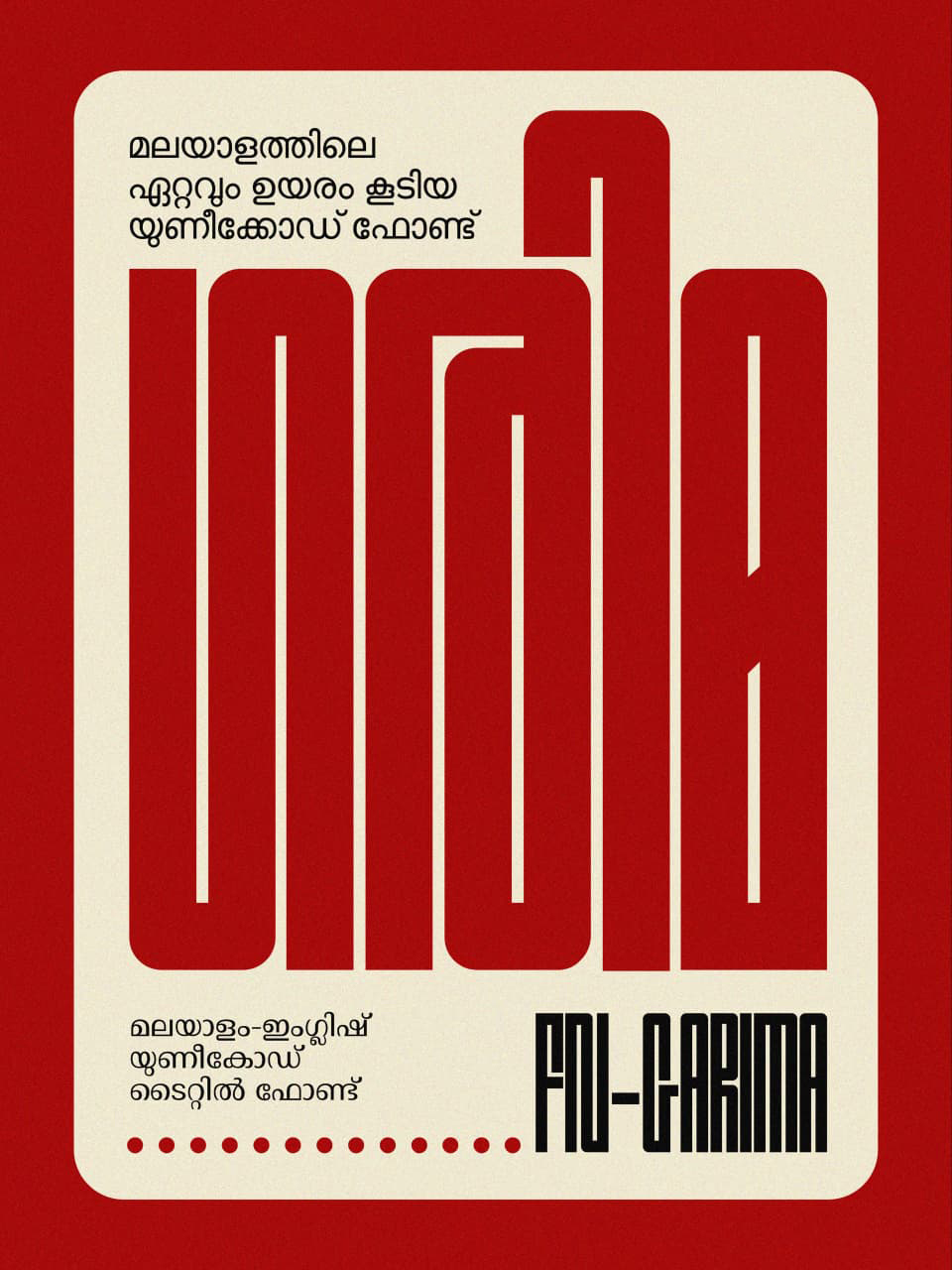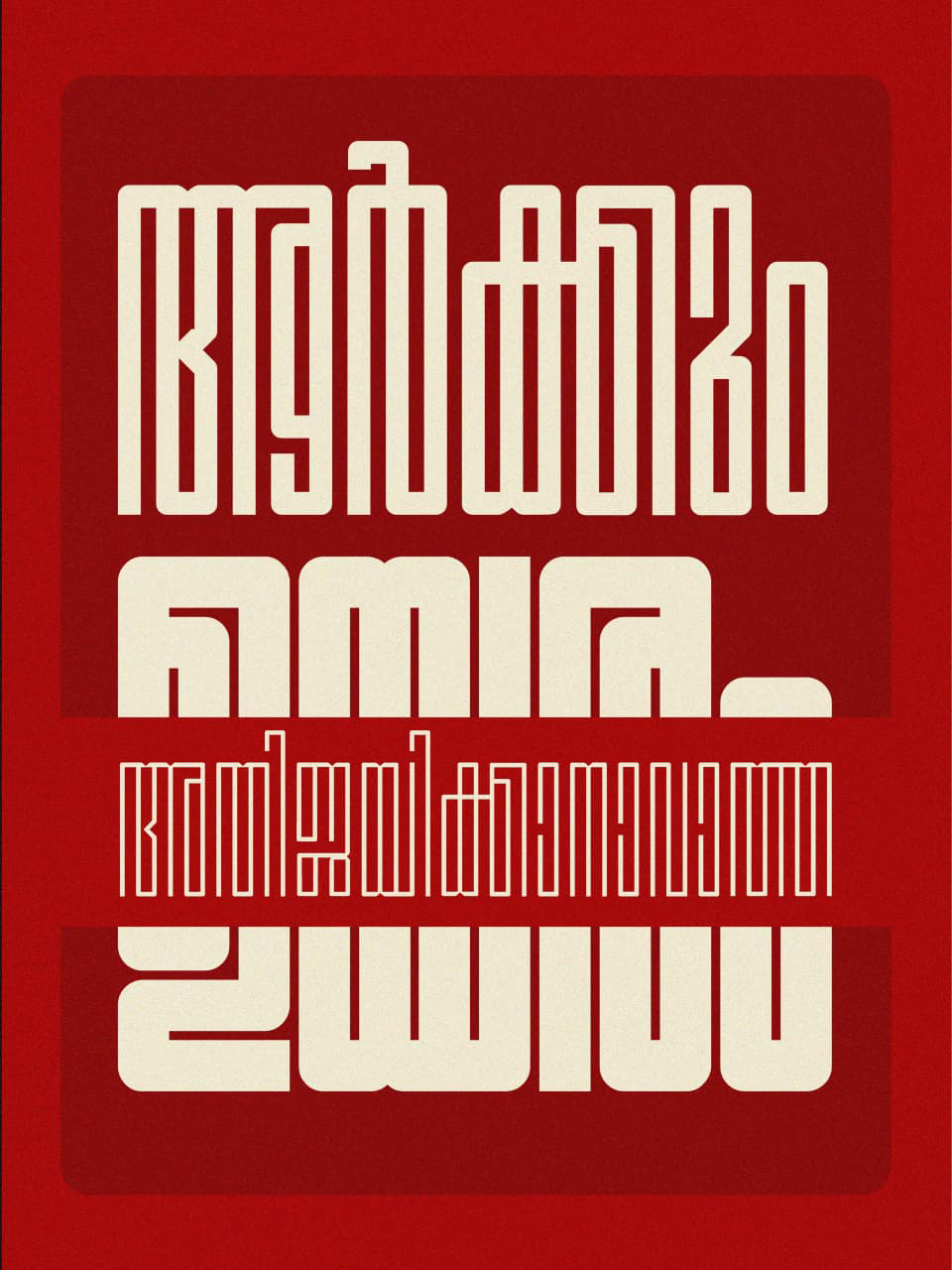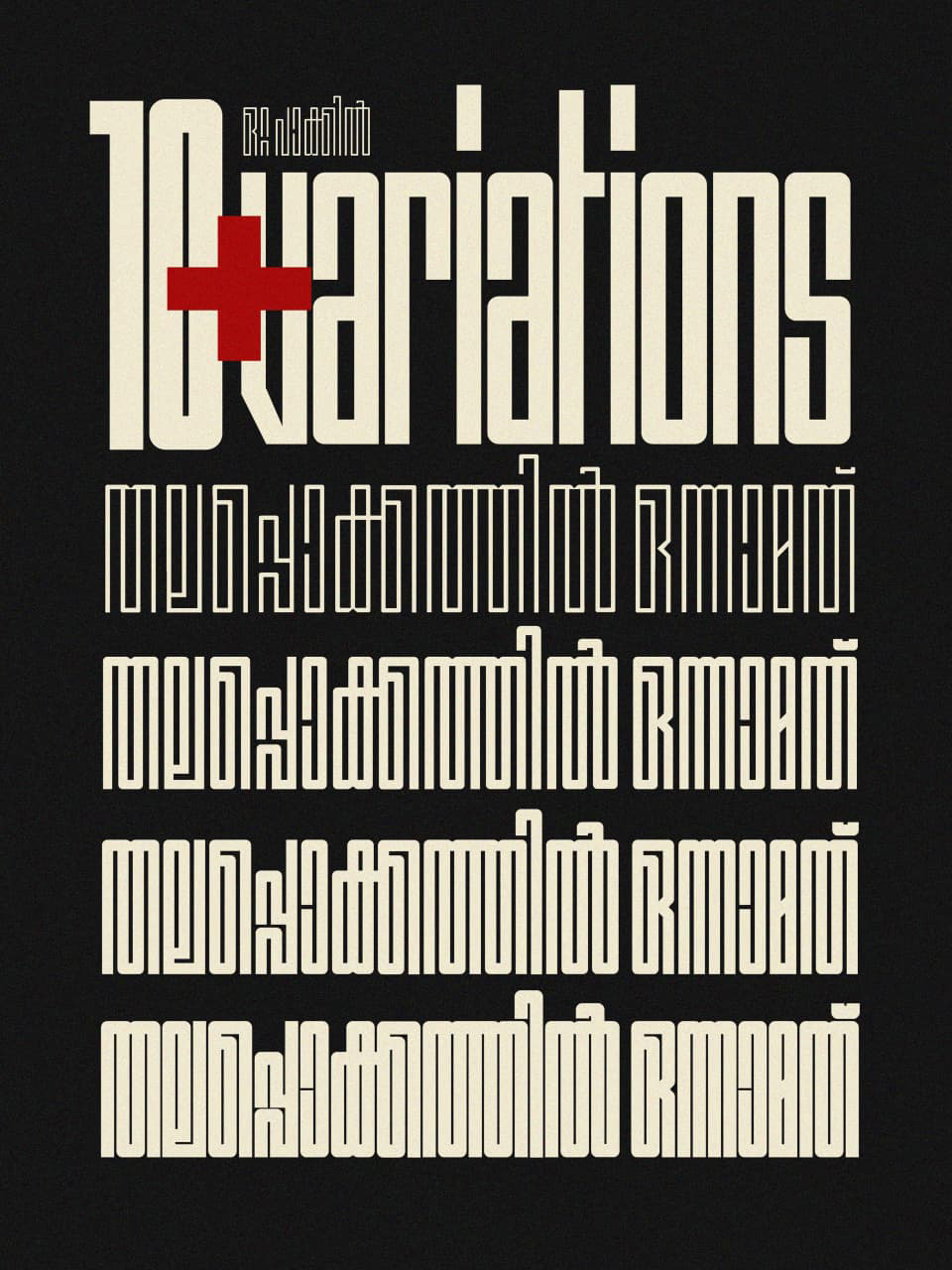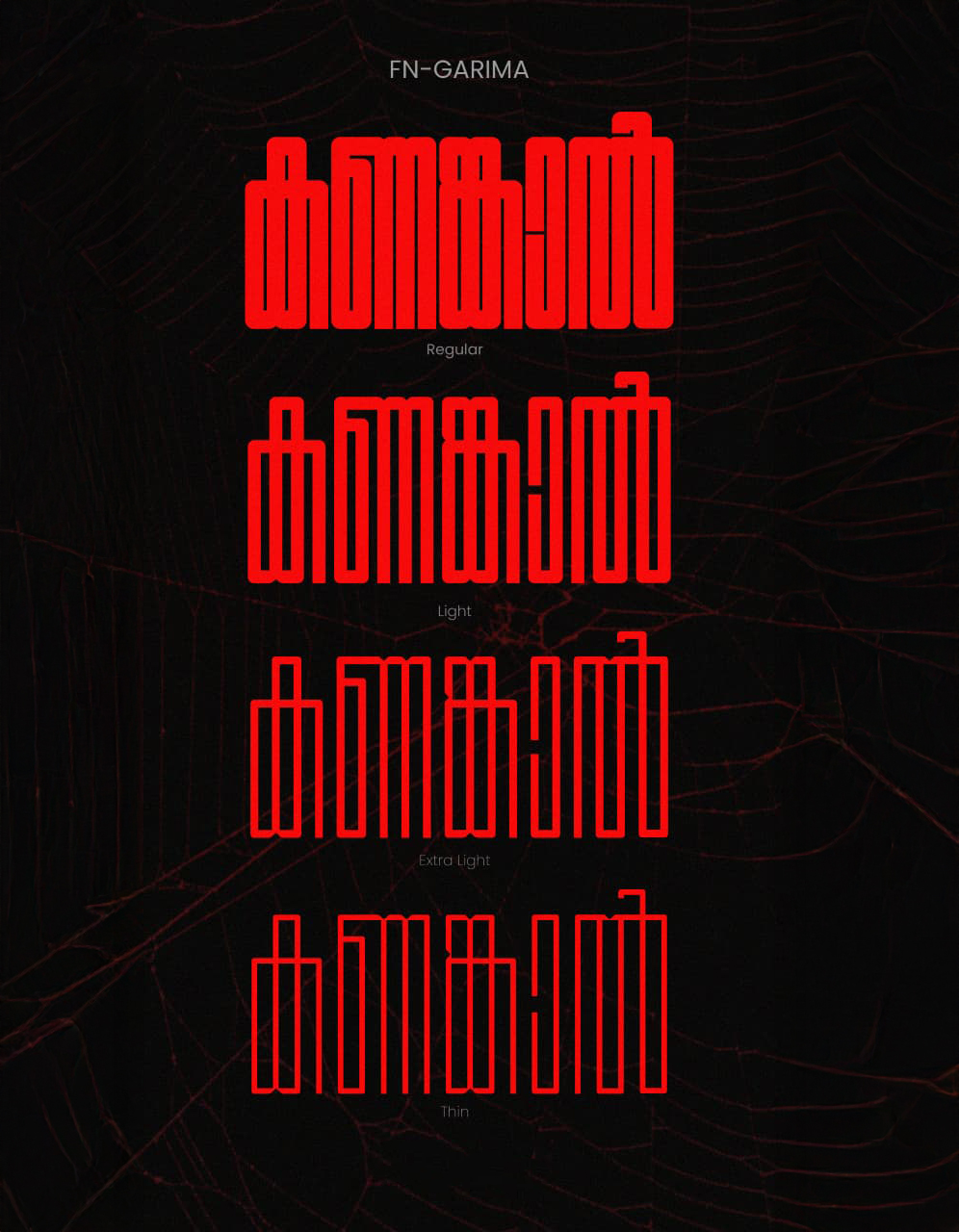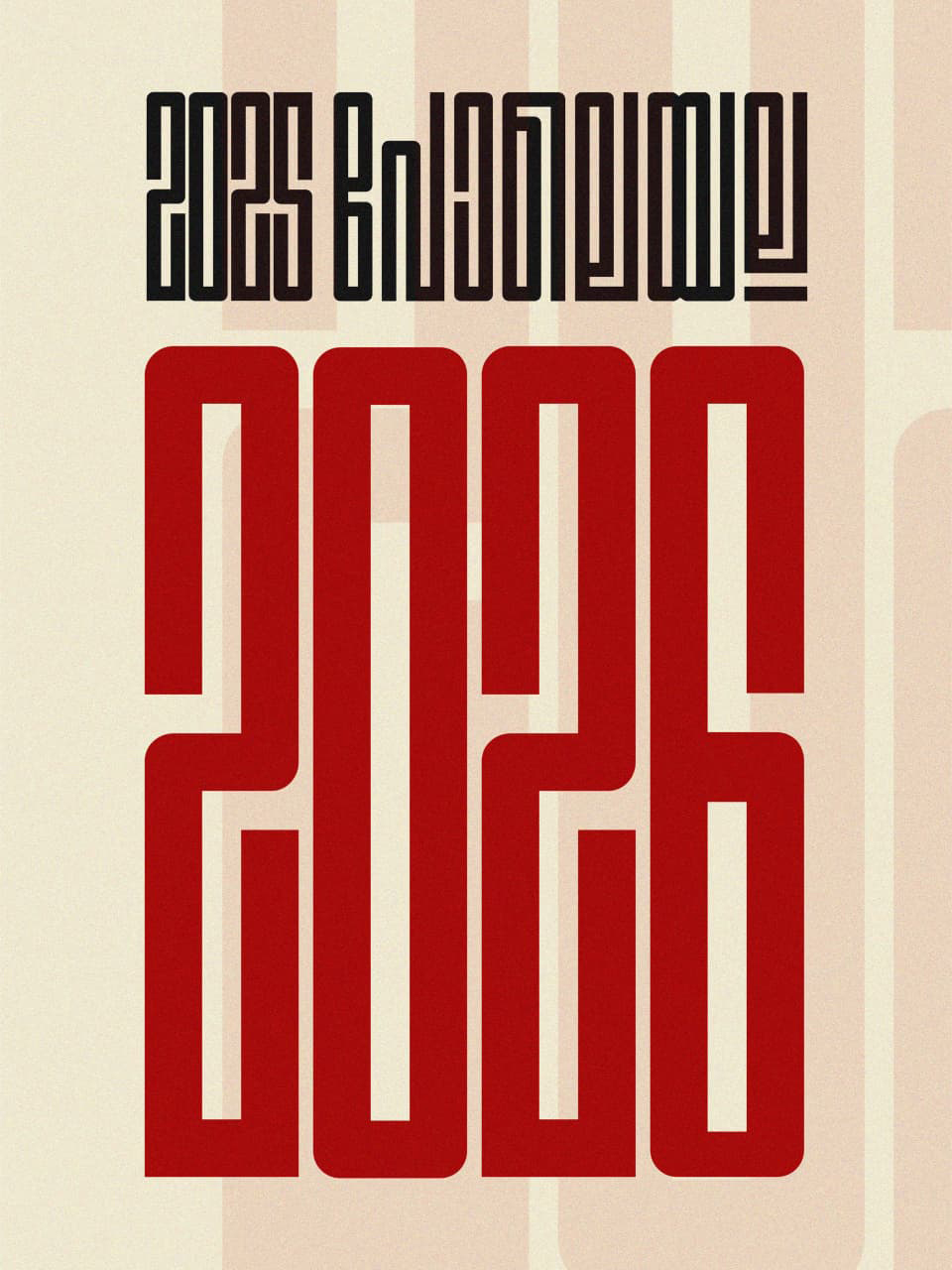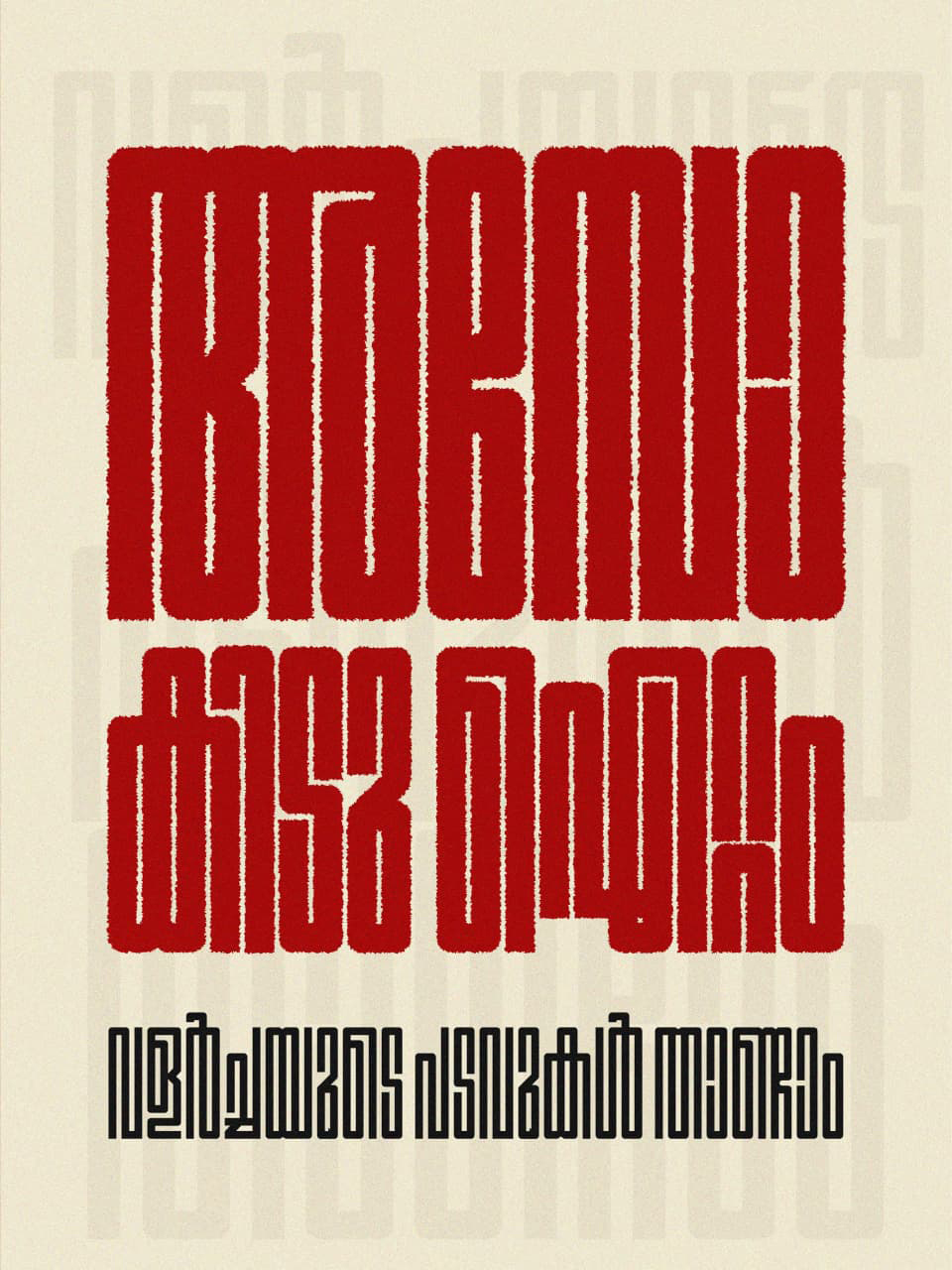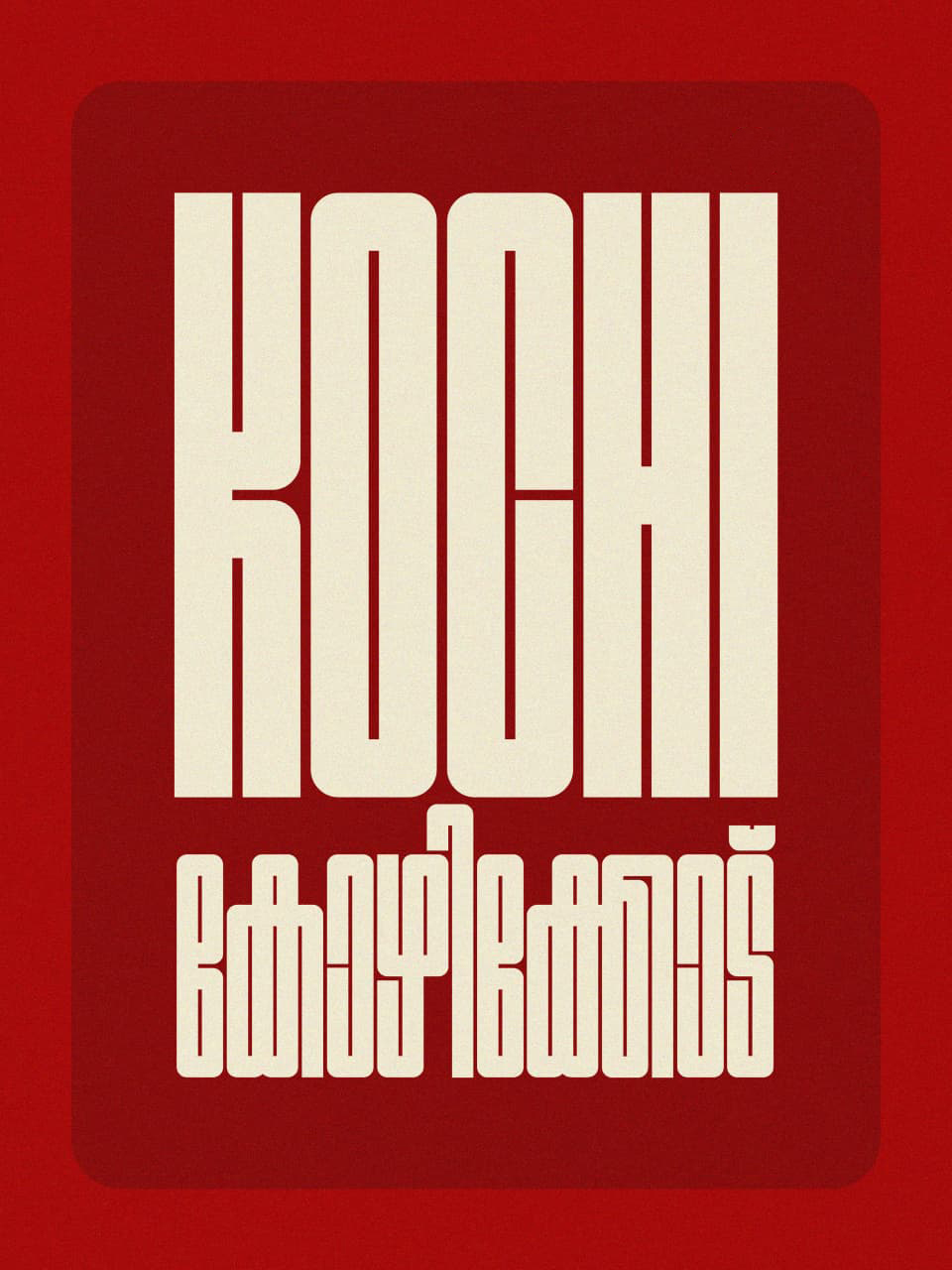
✨ മലയാളത്തിലെ ഏറ്റവും പുതിയ ഇംഗ്ലീഷ്-മലയാളം ബൈ ലിഗ്വൽ യുണീക്കോഡ് ടൈറ്റിൽ ഫോണ്ട്.
✨ ബുക്ക് കവർ, തിരഞ്ഞെടുപ്പ്, സ്പോർട്സ്, ആൽബം, ടി വി ഷോ എന്നിവയുടെ പോസ്റ്ററുകളിൽ മികച്ച ഓപ്ഷൻ.
✨ സ്പോർട്സ്, രാഷ്ട്രീയ, ടി വി താരങ്ങളുടെ ചിത്രങ്ങൾക്കൊപ്പം പേരോ ഷോർട് ടൈറ്റിലോ ചേർത്ത് ഡിസൈൻ ചെയ്യാൻ അനുയോജ്യമായ മലയാളത്തിലെ ഉയരംകൂടിയ ഫോണ്ട്. ബർത് ഡേ പോസ്റ്ററുകൾ, അഭിനന്ദനങ്ങൾ എന്നിവക്ക് മികച്ച ഓപ്ഷൻ.
✨ വലിയ ഹോർഡിങ്, പോസ്റ്റർ എന്നിവക്ക് അനുയോജ്യം.
✨ ഒറ്റ പാക്കേജിൽ തന്നെ റെഗുലർ, ലൈറ്റ്, എക്സ്ട്രാ ലൈറ്റ്, തിൻ, അവയുടെ ഇറ്റാലിക്, സ്ട്രിപ്, ഡിസ്ട്രോട്ട് തുടങ്ങിയ പത്തിലധികം സ്റ്റൈലുകൾ ലഭ്യം.
| Font Name | FN Garima |
| Font Type | Display & Title |
| Creator / Designer | Font Ashan |